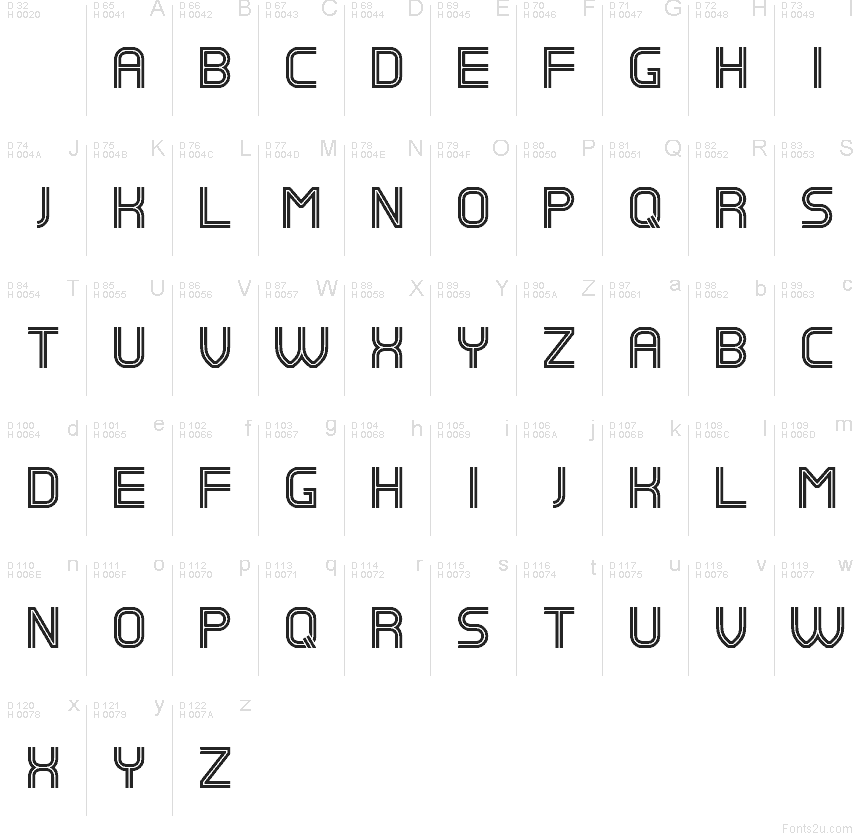
Catalog Retro di Vladimir Nikolic è un font display in stile retro, gratuito, che cattura la disinvoltura delle vecchie insegne e del design commerciale dei cataloghi per corrispondenza. Le maiuscole uniscono angoli arrotondati e spesse linee interne, rendendo le lettere corpose ma dal design curato, con un ritmo fluido e tubolare che mantiene l'estetica vintage leggera e mai pesante.
È perfetta per titoli di poster, packaging, menu in stile diner, copertine di dischi, bozzetti di loghi e brevi titoli editoriali in cui un tocco d'altri tempi aiuta a dare carattere al messaggio. Essendo un font gratuito, funziona bene anche per titoli e monogrammi, specialmente quando si vuole lasciare che le maiuscole a righe facciano stile da sole senza ulteriori ornamenti.